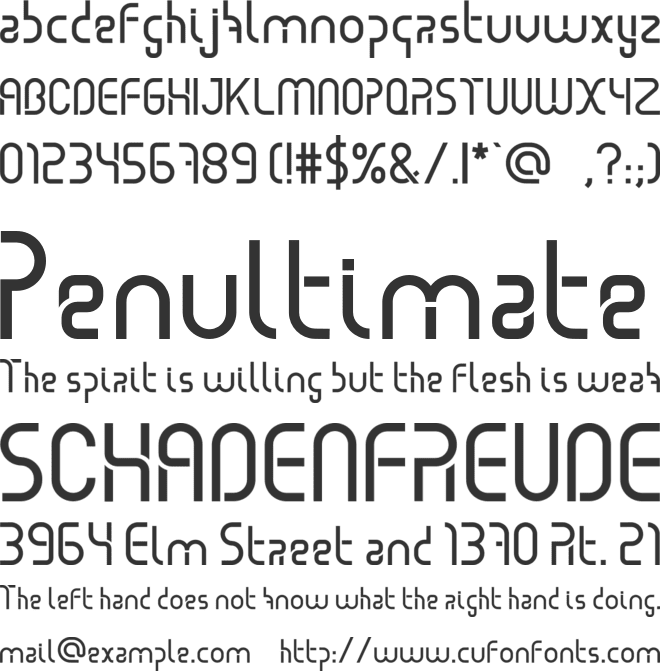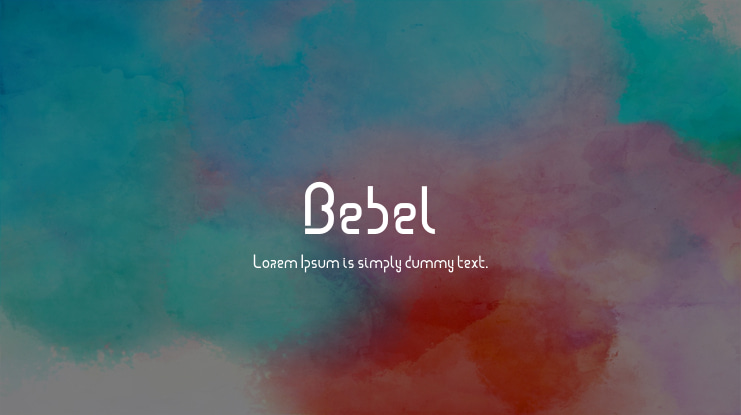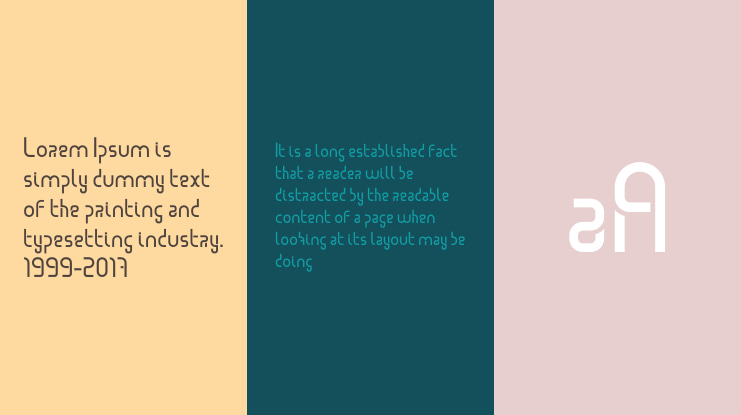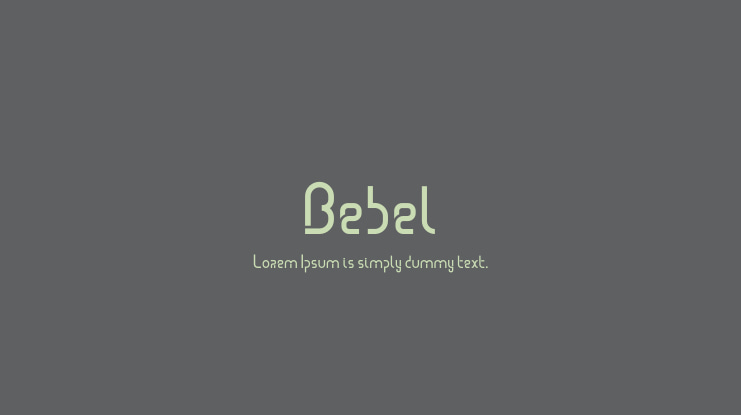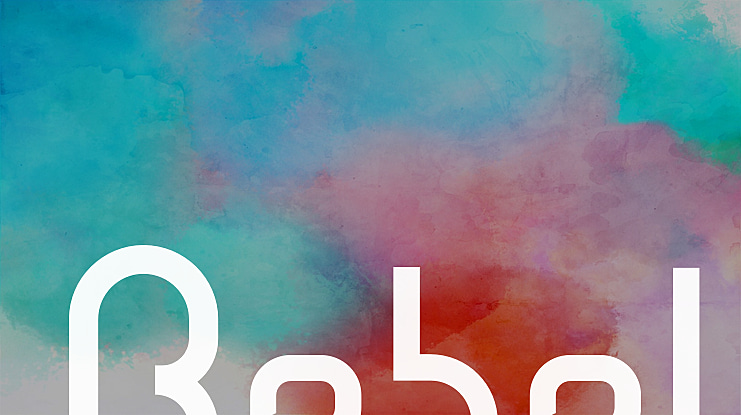
Bebel Font Family
J’adore travailler la typo, c’est un élément auquel je suis très sensible de manière générale, et je prends beaucoup de plaisir à en concevoir…
Un projet typo d’une envergure importante avec une multitudes de glyphes et graisses.
• 135 caractères : Capitale, minuscule, avec accents, chiffres, ponctuation… • 4 graisses : light, regular, bold, black
Cette nouvelle typo se prénomme « BEBEL » un petit clin d’oeil à mon papa ❤️
En effet Bebel était son surnom plus jeune, tiré de notre nom de famille « Belliot ». Mon père ne vient pas du tout du domaine artistique/com. etc… Mais il a toujours été de bon conseil pendant mes créations.
Lorsque j’habitais encore avec lui, j’avais pour habitude de lui montrer mes projets pour avoir son regard dessus, et ainsi pouvoir rebondir sur mes idées.